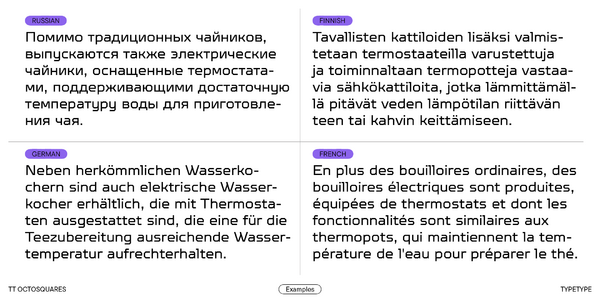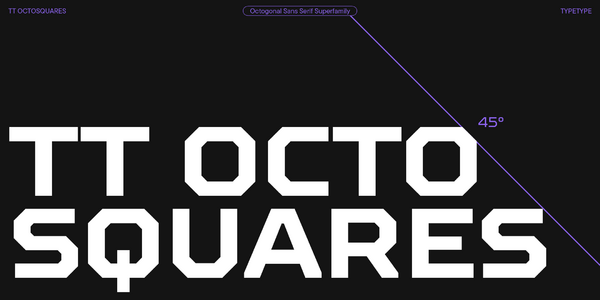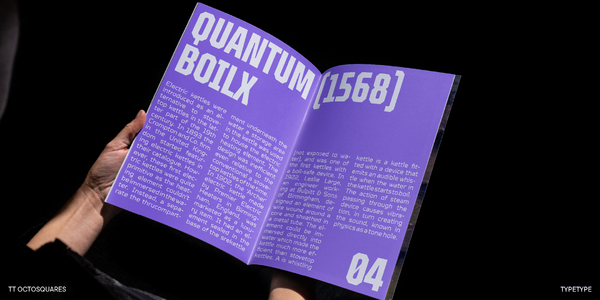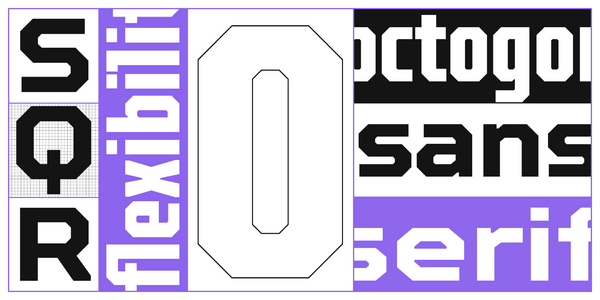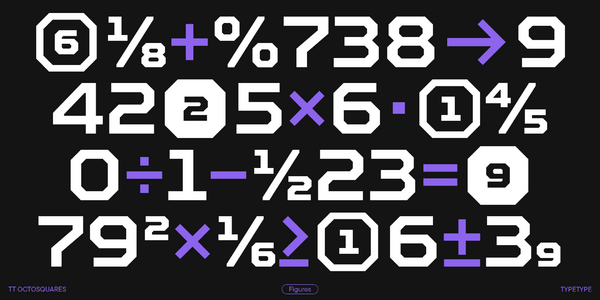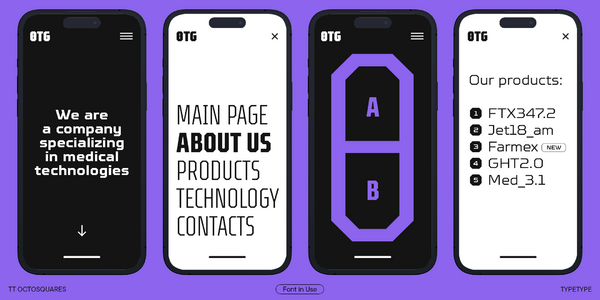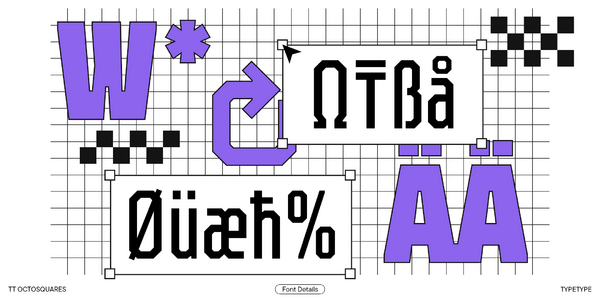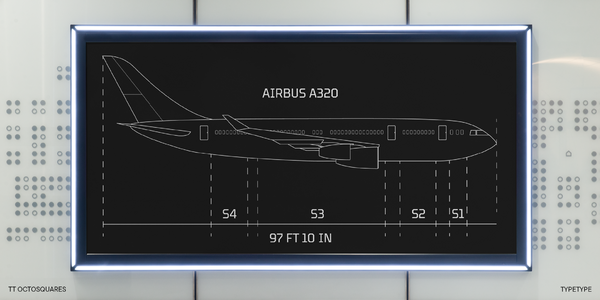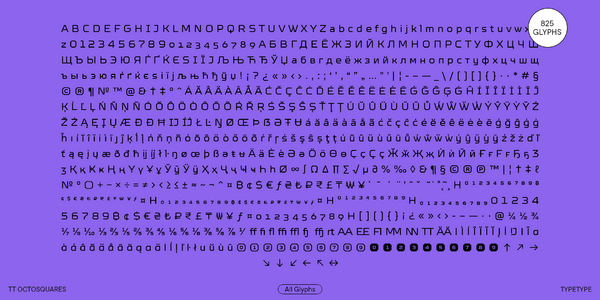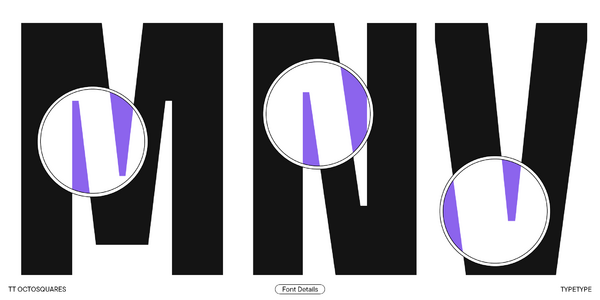
TT Octosquares
TT Octosquares — ТТ Октосквэрс
Произносится «ТТ Октосквэрс». «Octos» — производное слово от octa (с греческого «восемь») и «squares» — производное от square (с английского «квадрат»). Буквы «TT» являются аббревиатурой названия компании.
TT Octosquares — октагональный гротеск с футуристическим характером. Это акцидентный «мозаичный» шрифт, который выглядит так, будто собран из отдельных фрагментов.